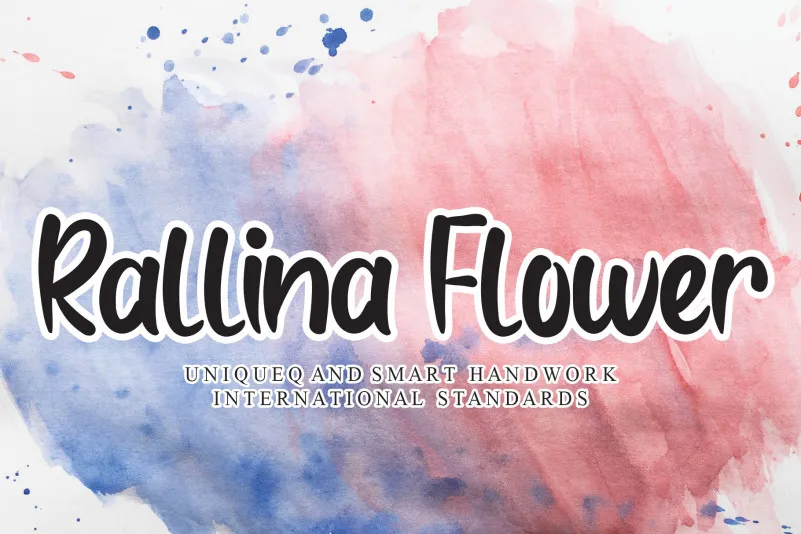
A ‘Rallina Flower Brush Font’ é uma elegante caligrafia casualeira que traz à vida seus projetos DIY. Inspirado no seu encanto visível, este estilo de fonte tem um toque delicado e casual que se encaixa perfeitamente em qualquer projeto pessoal ou artesanal. Com a ‘Rallina Flower Brush Font’, você pode adicionar um ar charmoso e único aos seus desenhos, gráficos e até mesmo aos teus projetos de escrita digital. Este é o ideal para quem procura uma fonte que transmite conforto e elegância, com uma paleta vibrante de cores e formas. Seja em sua própria arte ou no desenvolvimento de uma identidade visual, essa fonte certamente se encaixa perfeitamente em suas necessidades. Adquira a ‘Rallina Flower Brush Font’ hoje para dar mais vida à seus projetos DIY!